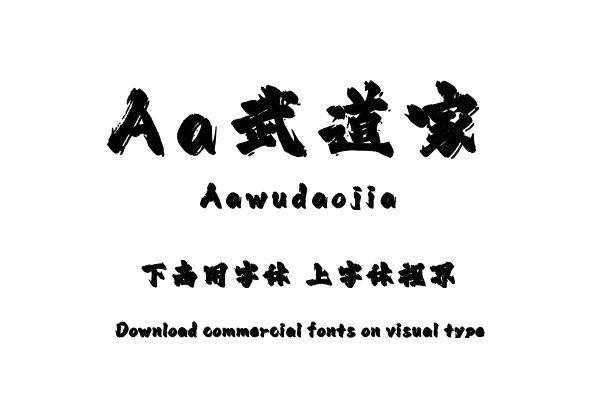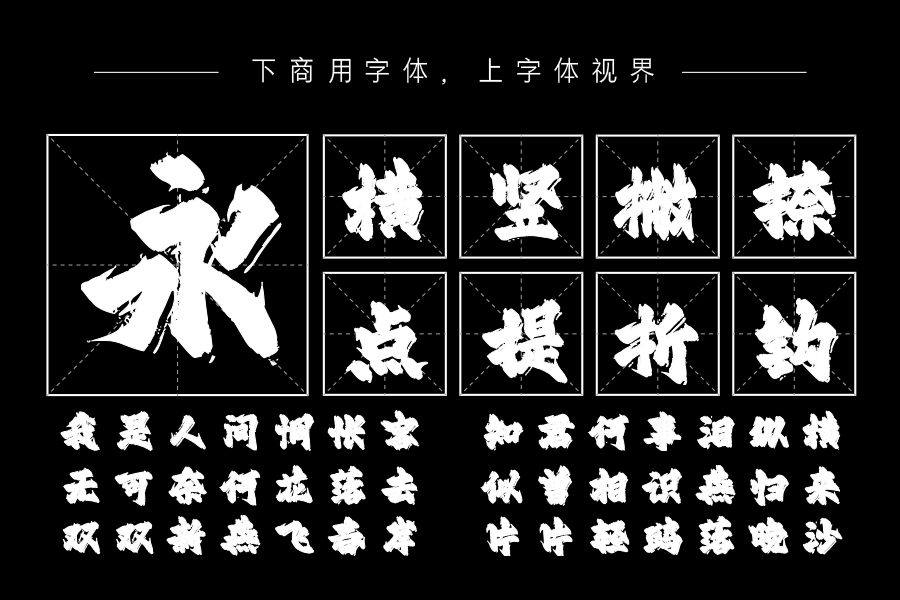
笔画粗重,线条刚硬,笔势凌厉有力,一笔一画的飞白,给人一种气吞山河的气势!笔画周围的附须更加突出整个字的游龙之势,完全通过手写的创作方式去勾勒出厚实有力的笔画,......购买须知:“下载服务费”与“字体VIP”所获得字体 仅用于个人非商用, 商用请联系付费授权。本字体为电脑用字,手机没有root权限不支持直接手机换字(手机如何root,请自行百度搜索教程)。购买前请先 了解清楚后再付款 ,字体为虚拟产品无法回收 一旦购买不支持退款。